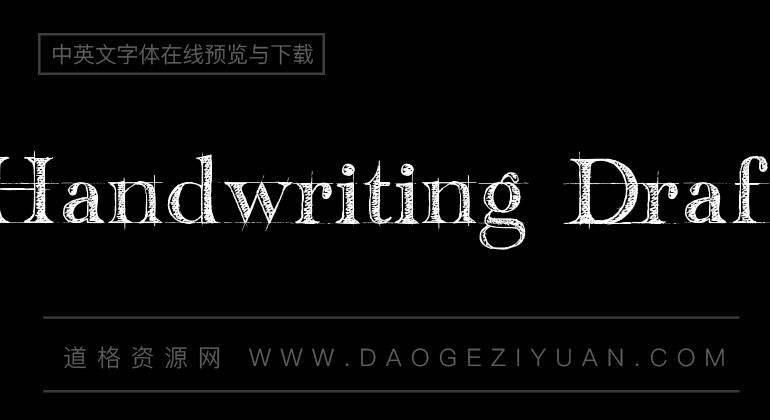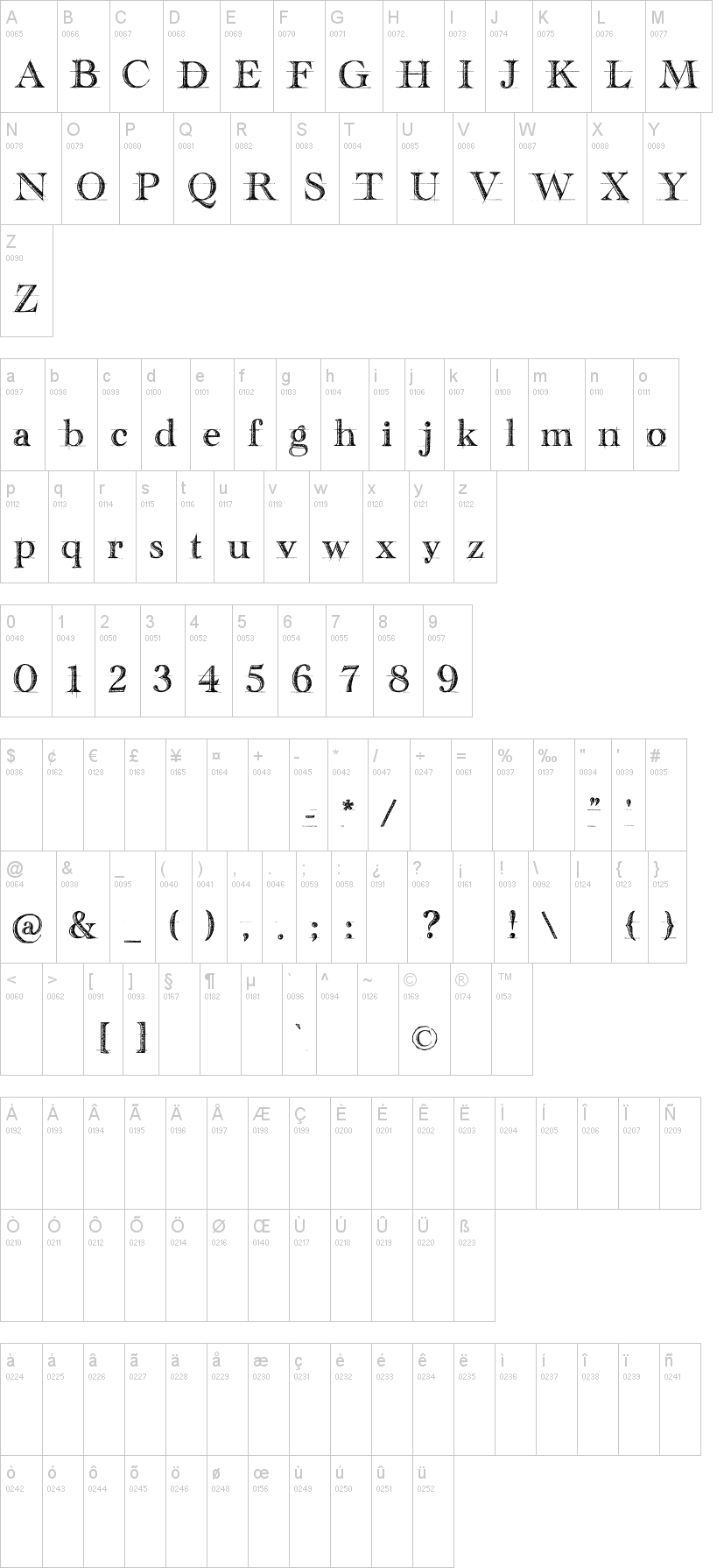
Handwriting Draft 是一款手写风格的字体,它具有自然、活泼、有趣的特点,能够更好地表达文字的意义,为您的文字添加更多的个性。它的字体特征有:每个字母和数字都有各自的笔画,且有明显的笔触,字形有自然的曲线,字体有自然的节奏感,线条有轻微的倾斜,每个字母的形状都有一定的灵活性,字体有着温暖的气息。内容介绍
Handwriting Draft是一款非常不错的手写艺术字体,具有很好的视觉感,适合于文化类的宣传设计、商业类品牌的广告和产品包装设计以及个性化文字排版等较多场景。